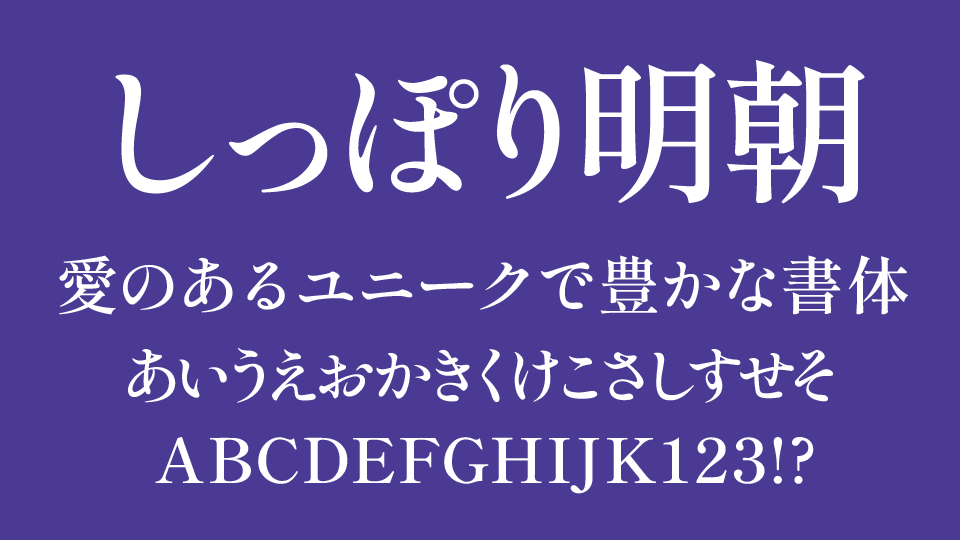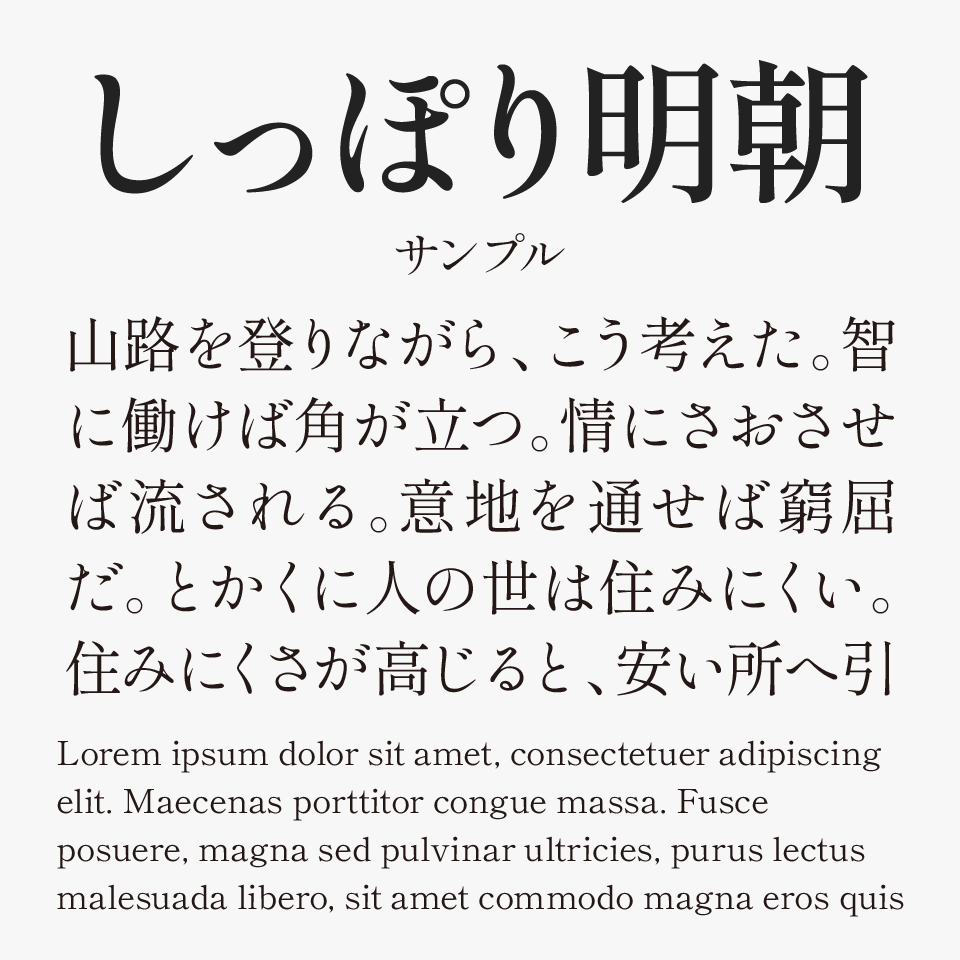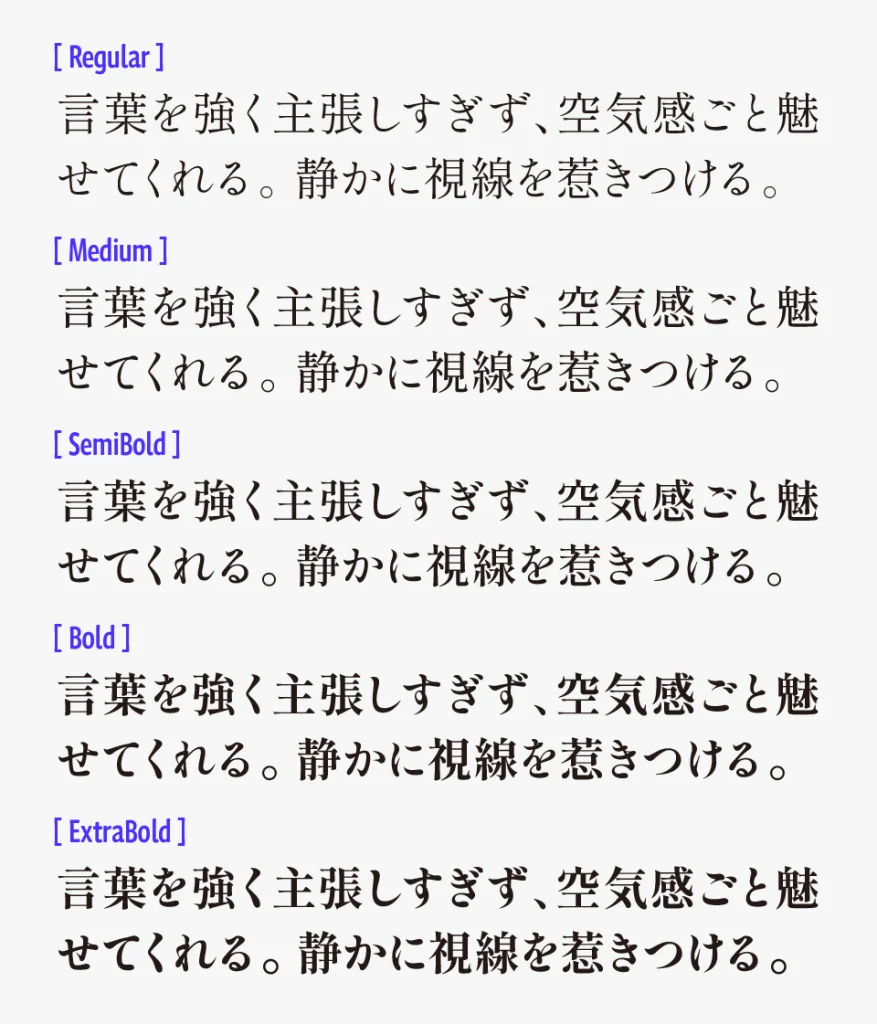
しっぽり明朝
しっぽり明朝フォントは、上品で落ち着いた空気感をまとい、見ているだけでうっとりするような雰囲気を目指して制作されたオールドスタイルの明朝体フォントです。
エッジや角にはやわらかな丸みが加えられており、明朝体特有の緊張感をほどよく和らげています。繊細さの中にやさしさがあり、どこか「しっぽり」とした情緒を感じられるところが魅力です。
クラシックな品格を持ちながらも堅苦しさはなく、和風デザインや文学的なビジュアル、落ち着いたタイトル表現にもぴったりなフォントです。
非常に整っており、品質が高いのにフリーフォントで良いのか疑ってしまうほど、完成度が高い明朝体フォントです。
また、ウェイト(太さ)が5種類用意されているため、細めの本文用途から存在感のあるタイトルデザインまで、幅広いシーンで使いやすです。用途に合わせて印象を調整しやすく、統一感を保ちながらデザインへ取り入れやすいフォントとなっています。
収録文字は、ひらがな・カタカナ・漢字・記号・英数字を含む約14,000字程度が収録されているとのことです。